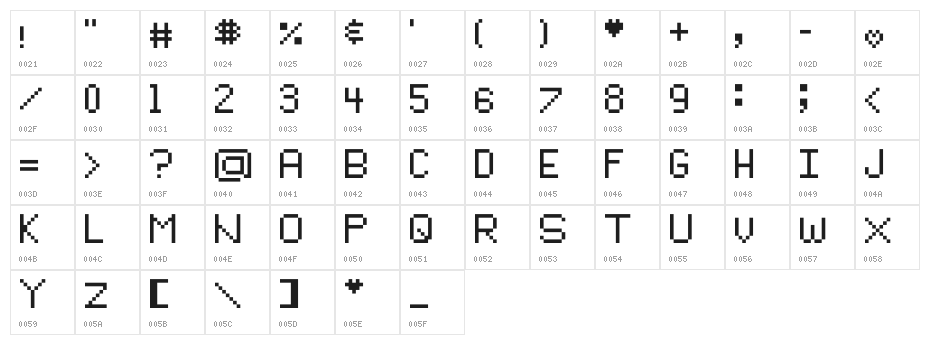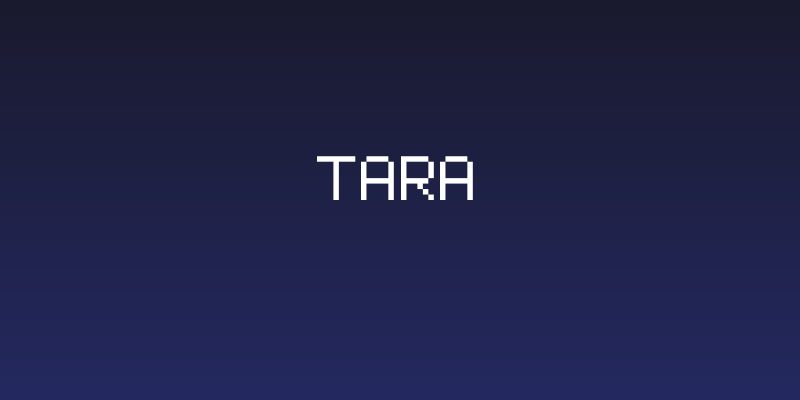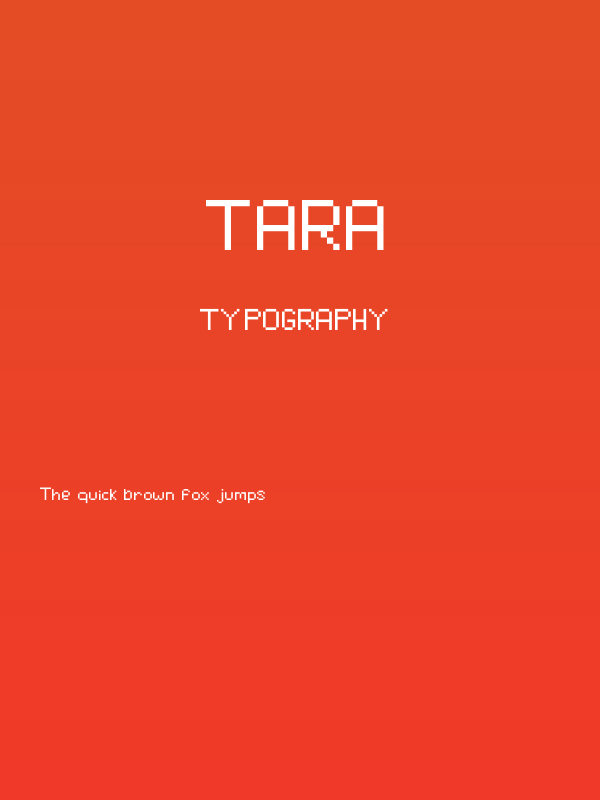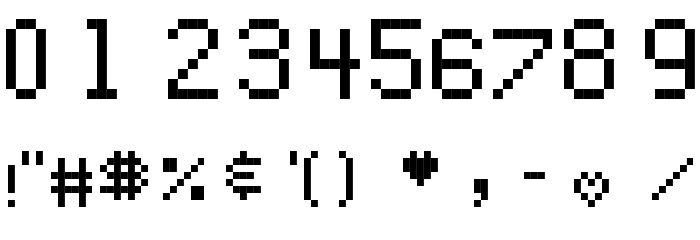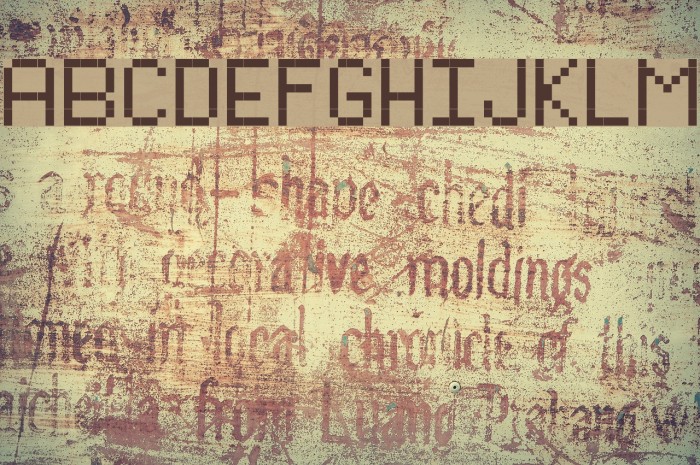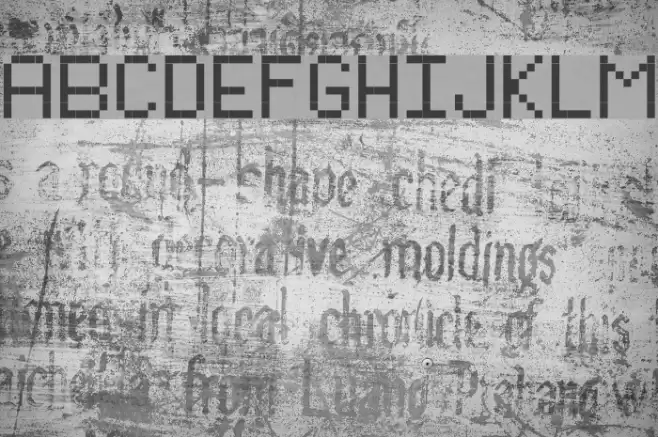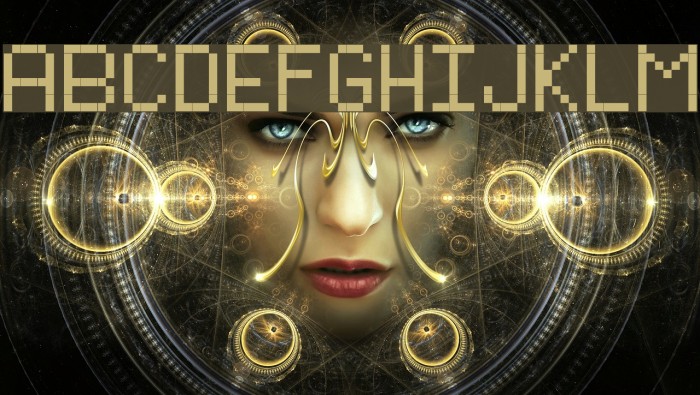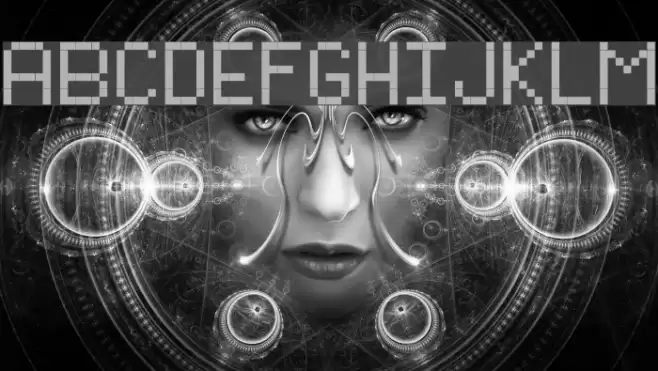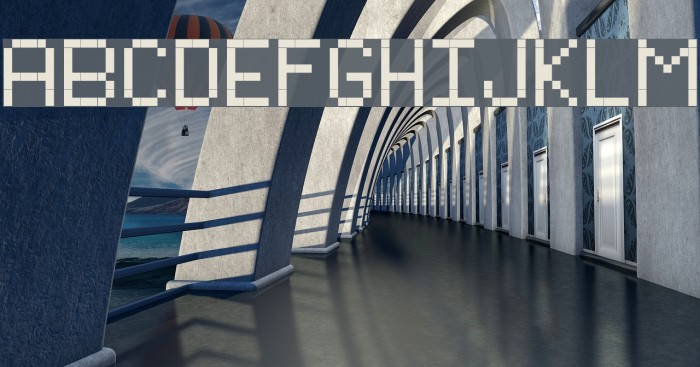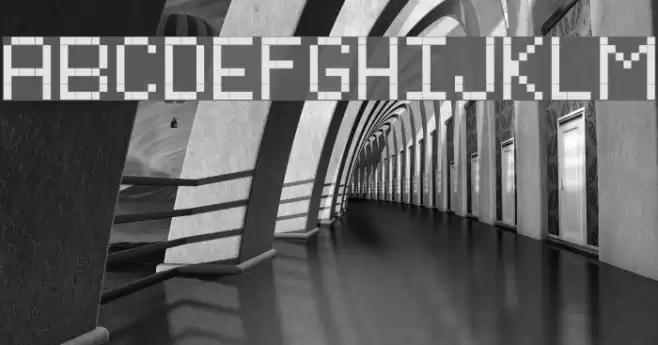
tara Font
✎ Pixel
| Gesamtstil | Retro, Digital |
| Anwendungsfall | Logos, Headlines, Digital displays |
| Vorgeschlagene Projekte | Ideal for retro video game graphics, digital-themed posters, pixel art projects, and any design that requires a nostalgic digital aesthetic. |